Cách để đổi font chữ trên Google Chrome
Bước 1: Trong trình duyệt Chrome, click vào nút 3 chấm ở góc trên bên phải màn hình.
Bước 2: Trong menu vừa xổ ra, click vào mục Settings ở gần cuối
Bước 3: Một tab mới sẽ mở ra trong Chrome. Đây là cửa sổ cài đặt nên bạn có thể tùy chỉnh gao diện Chrome. Trong danh sách bên trái, click vào mục Appearance, rồi kéo xuống và click vào mục Customize Fonts.
Hoặc, bạn có thể copy paste dòng này chrome://settings/fonts vào thanh địa chỉ web để được đưa thẳng tới menu font.
Bước 4: Trong mục Customize Fonts, bạn sẽ thấy có những lựa chọn sau:
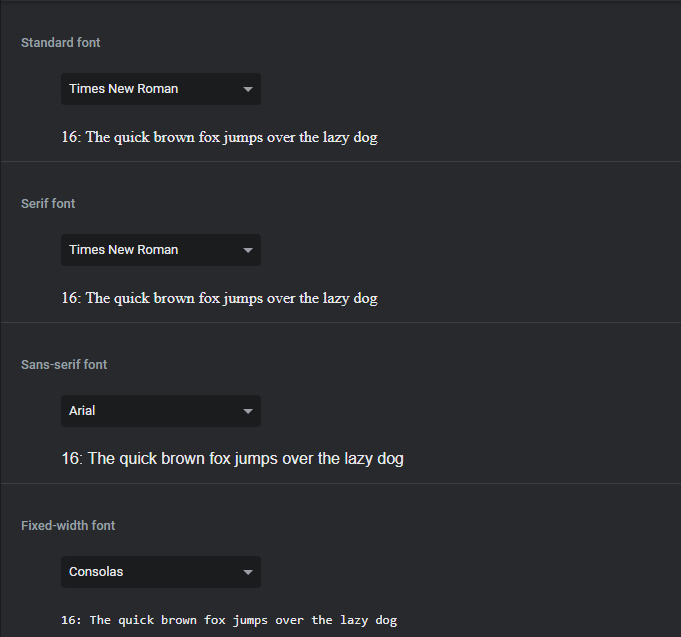
Standard: Loại font chữ kích cỡ nhỏ và có dấu móc ở cuối mỗi kí tự. Ví dụ gồm các font Times Roman, Courier, và Palatino.
Sans-serif: Loại font chữ không có dấu móc ở cuối mỗi kí tự, dành cho những người thích kiểu chữ tối giản. Ví dụ gồm Helvetica, Avant Garde, và Geneva.
Fixed width: Lựa chọn này cho phép thay đổi khoảng cách giữa các từ, kí tự và câu trong một đoạn văn. Nếu bạn thấy chữ hiển thị trong trình duyệt quá sát nhau thì đây là một tính năng rất hữu dụng.
Với mỗi lựa chọn trên, bạn có thể tùy ý chọn loại font mình thích, và ngoại hình thật của font cũng sẽ hiện ra ngay bên dưới tên font như trên hình để bạn tiện lựa chọn. Số lượng font trong Chrome cũng rất nhiều và đa dạng chẳng kém gì trong Word, nên bạn sẽ dễ dàng chọn được một font chữ phù hợp cho mình.